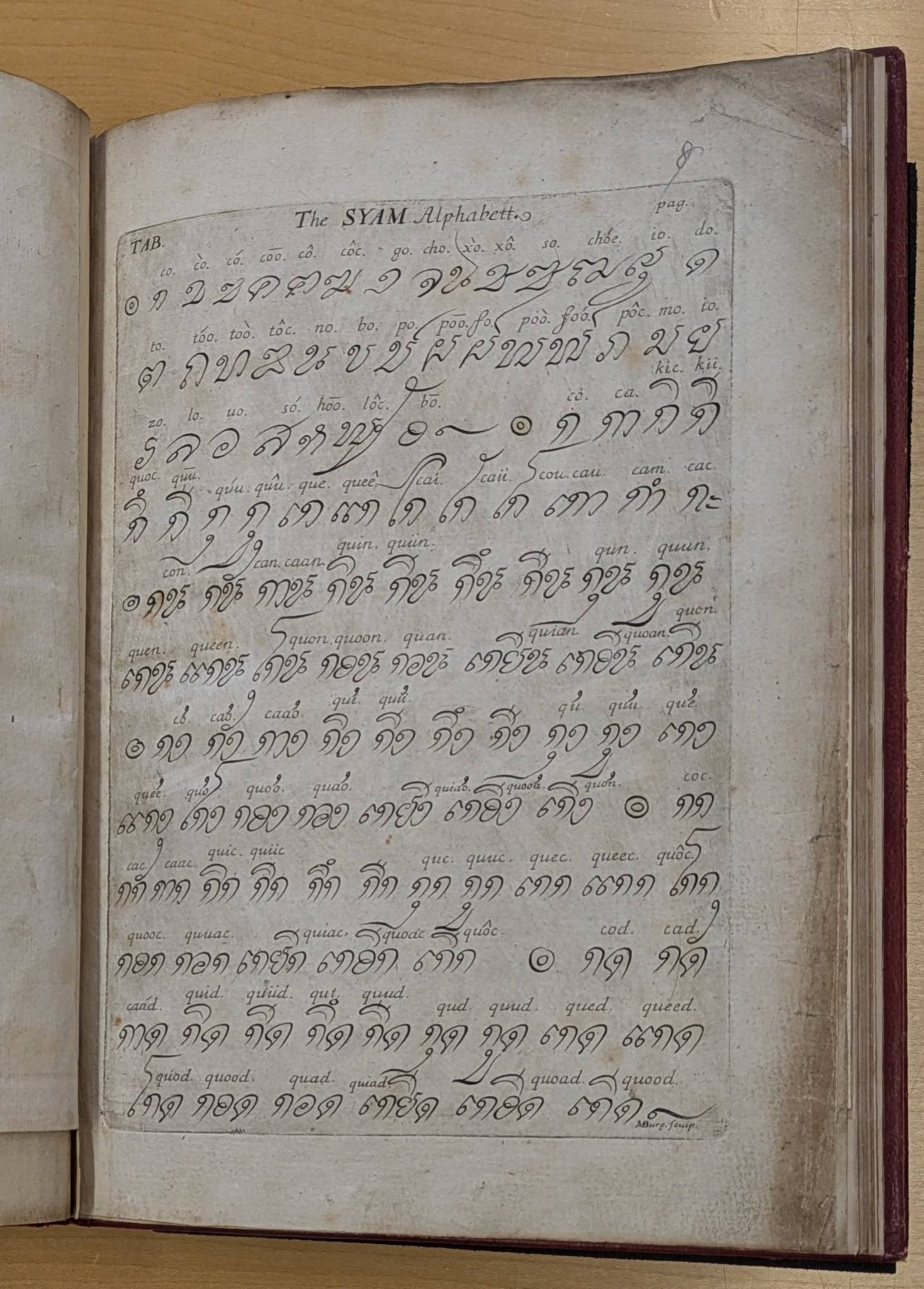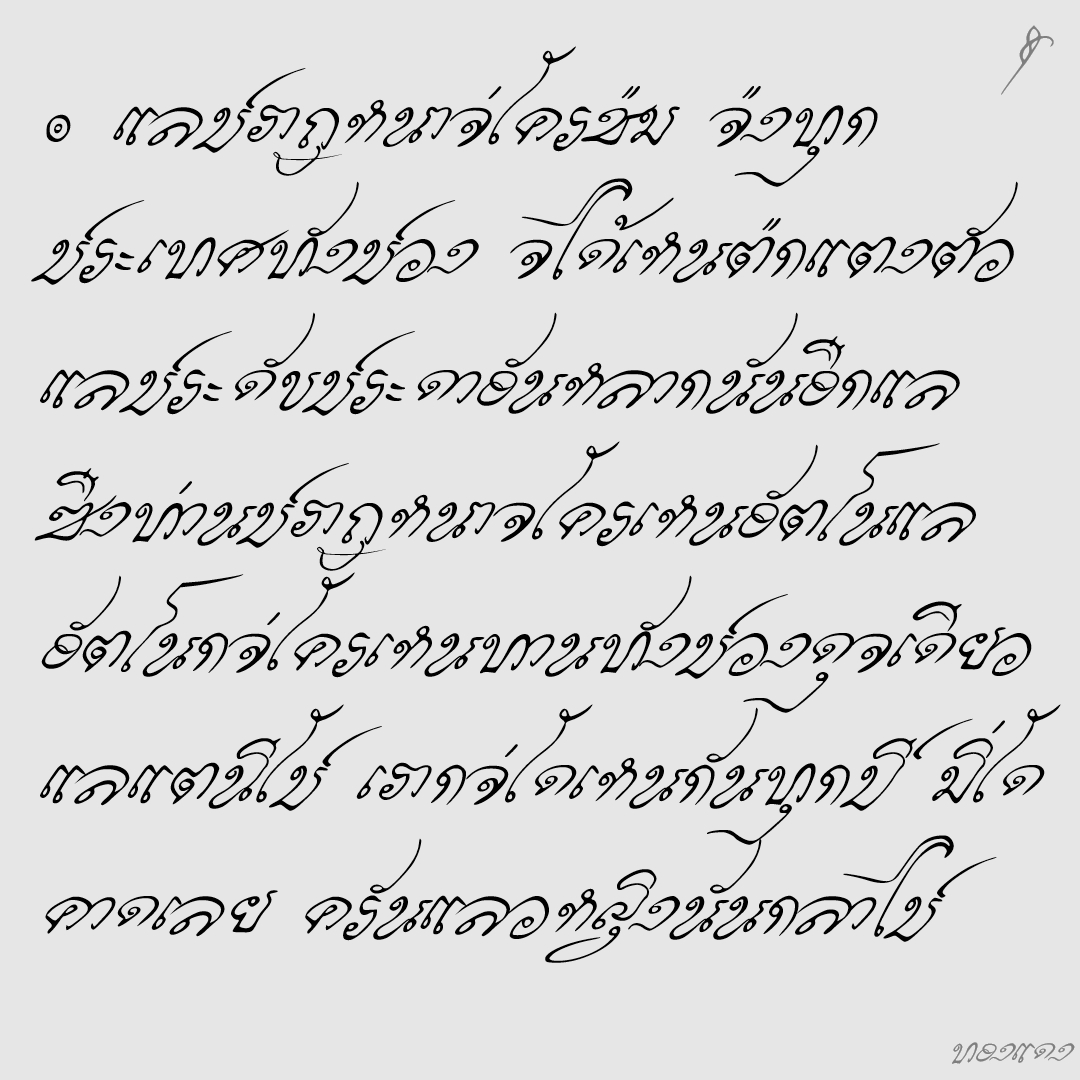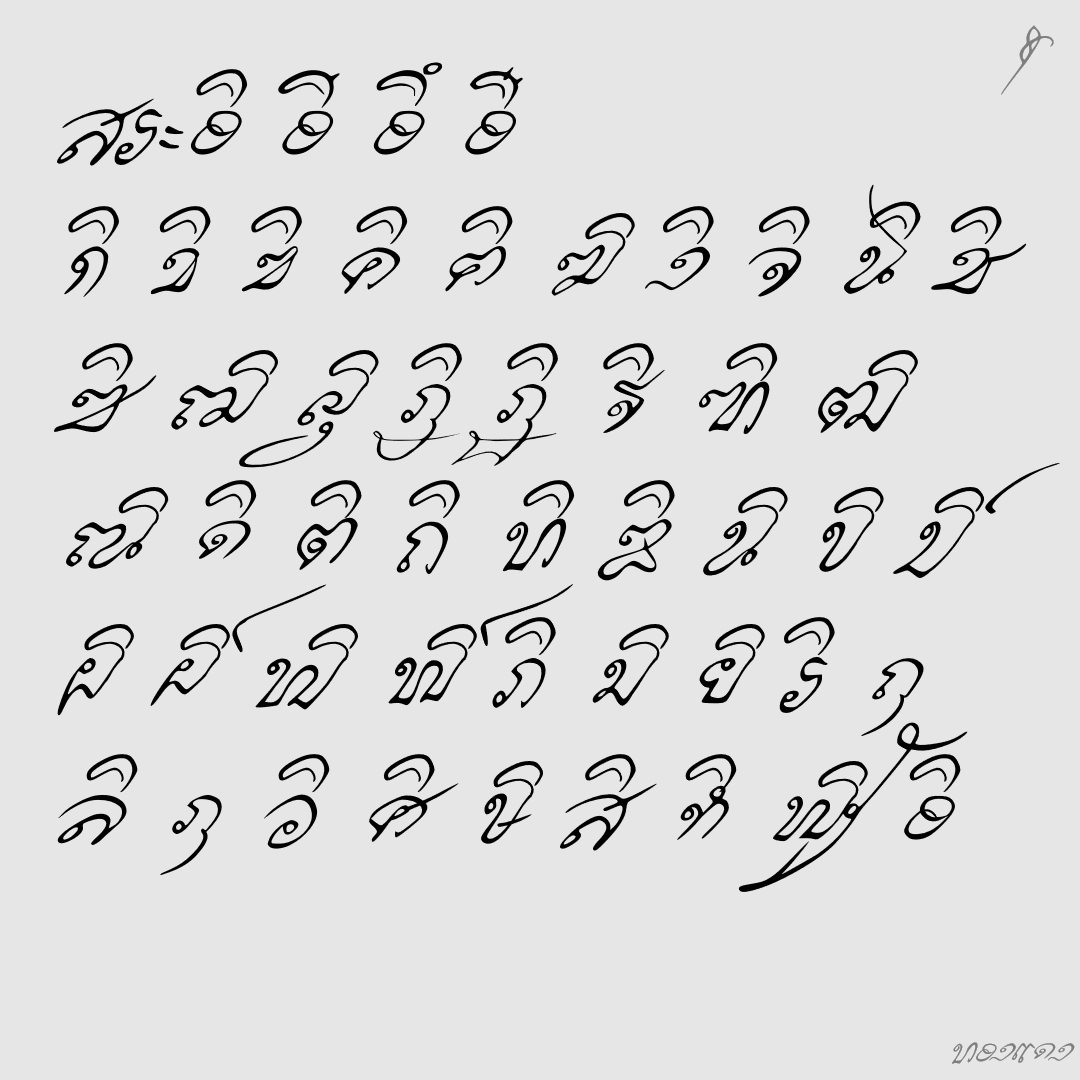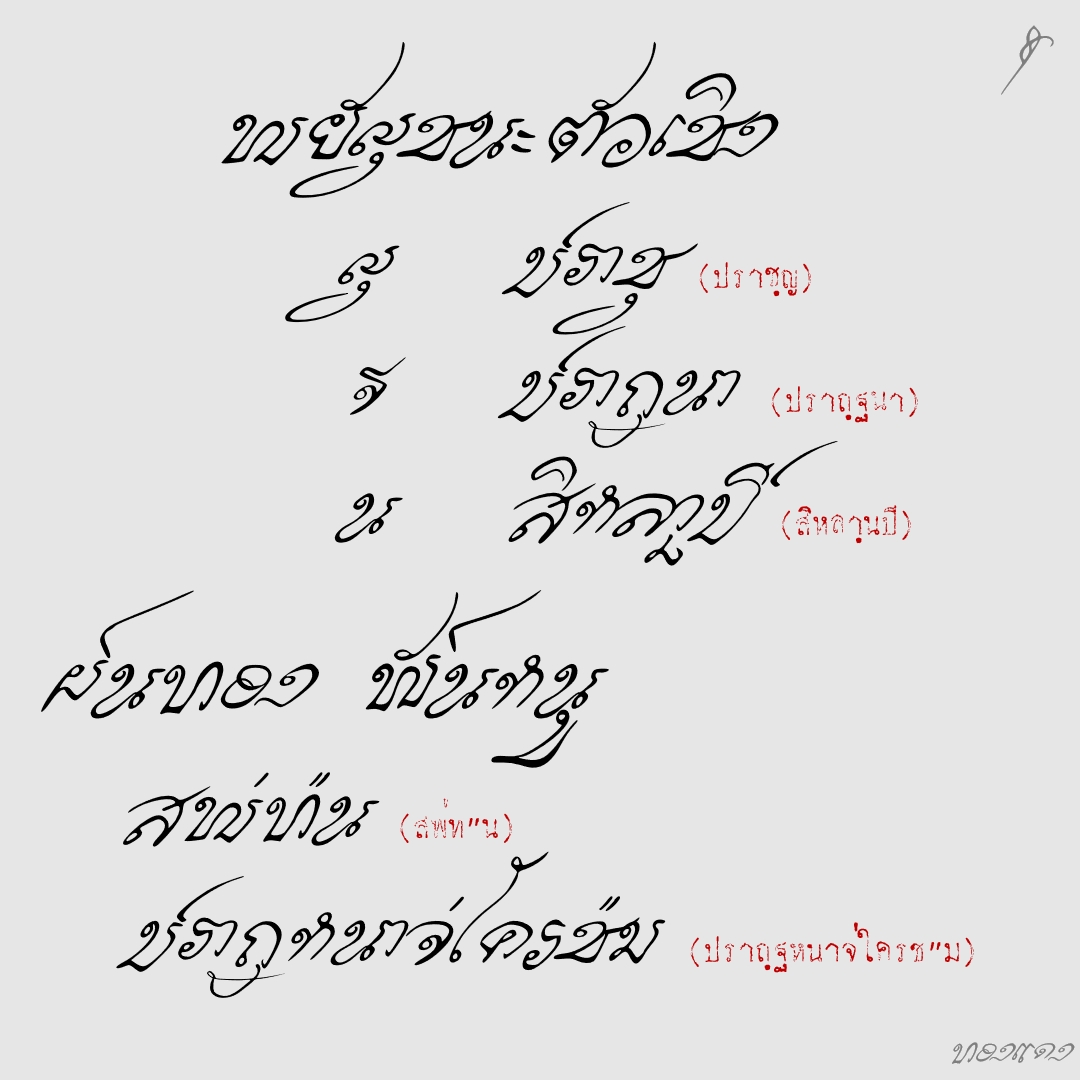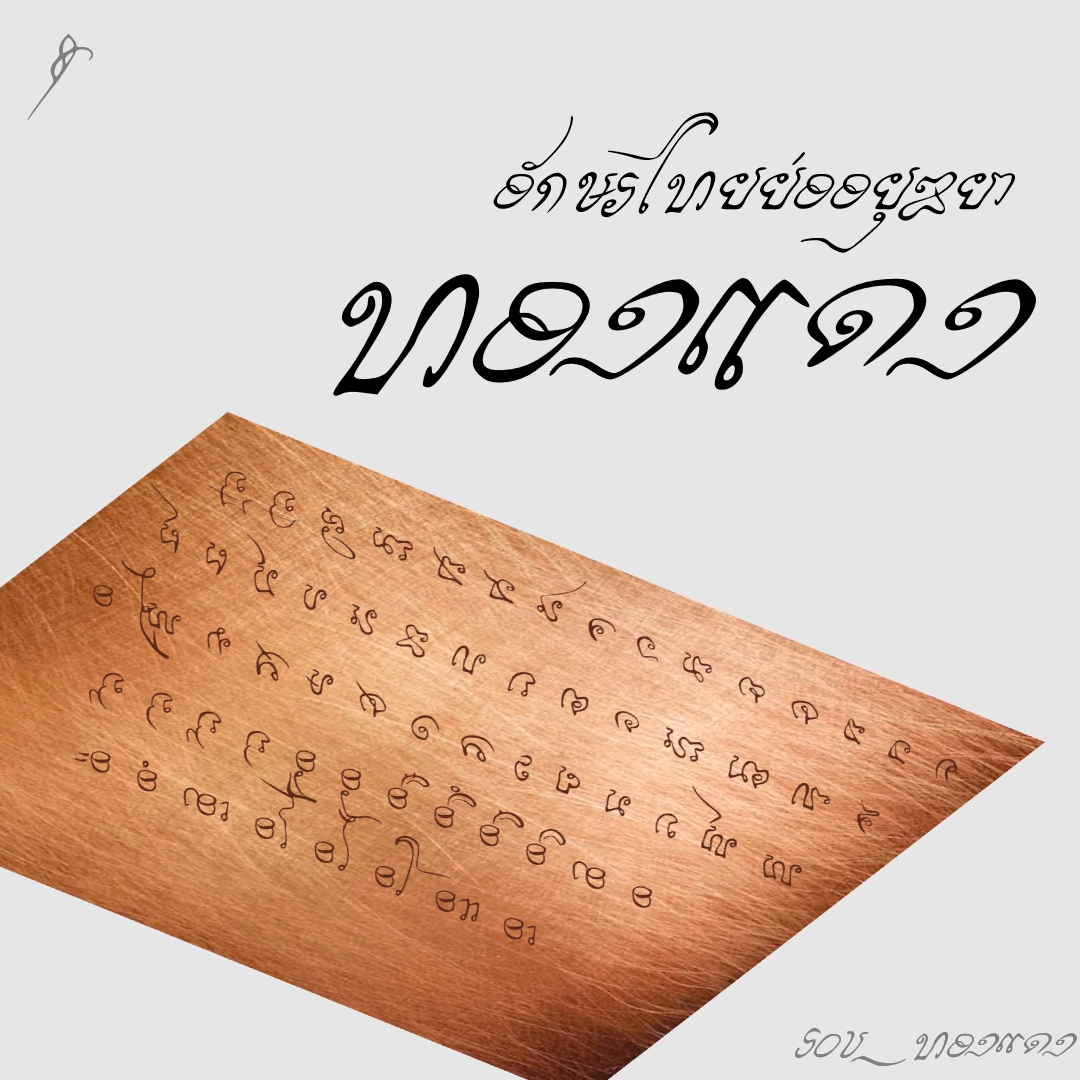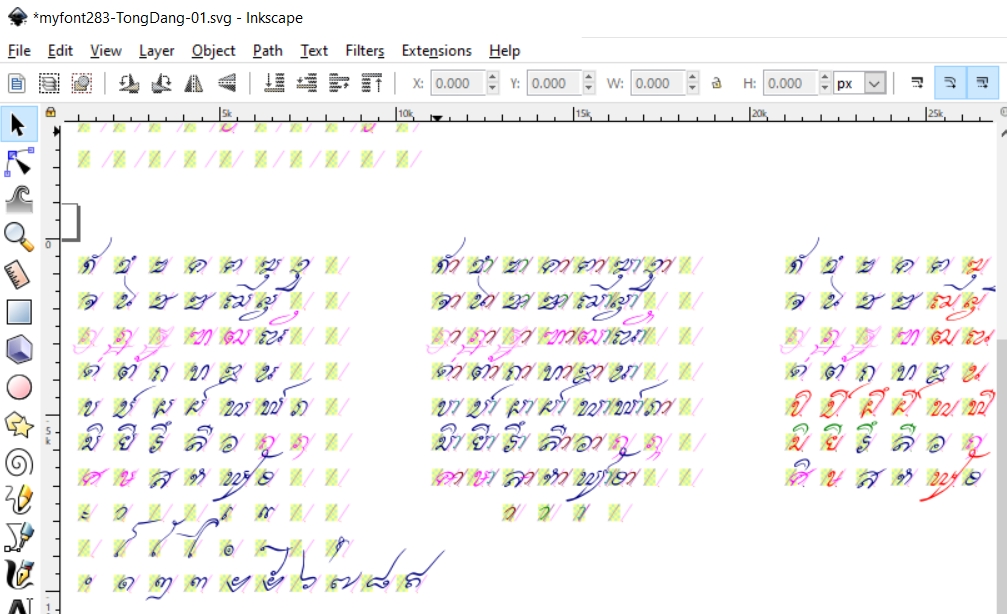
ฟอนต์ ทองแดง
ฟอนต์ทองแดง เป็นฟอนต์ที่จินตนาการว่าถ้าฝรั่งยุโรปที่เข้ามาในแผ่นดินสมเด็จพระนารายณ์ เขียนอักษรไทยอยุธยาหน้าตาน่าจะประมาณนี้ (ถ้าผู้รู้มีคำแนะนำเพิ่มเติมบอกได้นะครับ)
หมายเหตุ รูปแบบตัวอักษรหลักๆจากภาพพิมพ์ทองแดง ‘The SYAM Alphabett.’ โดย Michael Burghers เมื่อ 300กว่าปีที่แล้ว โดยอักษรดังกล่าว อ้างอิงมาจาก อักษรที่เขียนด้วยลายมือถวายพระเจ้าชาร์ลส์ที่ 2 ในปี ค.ศ.1684 แต่ในแบบดังกล่าวยังมีอักษรไม่ครบถ้วนในยุคนั้น ผมจึงได้เพิ่มอักษรเข้าไป โดยอิงจาก ‘Trois Alphabeth Siamois.’ โดย La Loubere  จดหมายเหตุลาลูแบร์พิมพ์ปี ค.ศ. 1691 ,เอกสารประชุมจดหมายเหตุออกพระวิสูทสุนทร(โกษาปาน) พ.ศ. ๒๒๓๑ (ประมาณ ค.ศ. 1688)  และนิราศต้นทางฝรงงเสษ พ.ศ. ๒๒๒๙ (ประมาณ ค.ศ. 1686)  ส่วนในวรรค ฏ ที่ไม่พบนั้น ผมจินตนาการรูปแบบอักษรขึ้นมาเองเพื่อให้ครบถ้วนตามยุคสมัย โดยอิงจากจารึกในปี พ.ศ.ใกล้เคียงกัน
ทองแดง
ชื่อฟอนต์ : ทองแดง
ฟอนต์ทองแดง เป็นฟอนต์ที่จินตนาการว่าถ้าฝรั่งยุโรปที่เข้ามาในแผ่นดินสมเด็จพระนารายณ์ เขียนอักษรไทยอยุธยาหน้าตาน่าจะประมาณนี้ (ถ้าผู้รู้มีคำแนะนำเพิ่มเติมบอกได้นะครับ)
หมายเหตุ รูปแบบตัวอักษรหลักๆจากภาพพิมพ์ทองแดง ‘The SYAM Alphabett.’ โดย Michael Burghers เมื่อ 300กว่าปีที่แล้ว โดยอักษรดังกล่าว อ้างอิงมาจาก อักษรที่เขียนด้วยลายมือถวายพระเจ้าชาร์ลส์ที่ 2 ในปี ค.ศ.1684 แต่ในแบบดังกล่าวยังมีอักษรไม่ครบถ้วนในยุคนั้น ผมจึงได้เพิ่มอักษรเข้าไป โดยอิงจาก ‘Trois Alphabeth Siamois.’ โดย La Loubere  จดหมายเหตุลาลูแบร์พิมพ์ปี ค.ศ. 1691 ,เอกสารประชุมจดหมายเหตุออกพระวิสูทสุนทร(โกษาปาน) พ.ศ. ๒๒๓๑ (ประมาณ ค.ศ. 1688)  และนิราศต้นทางฝรงงเสษ พ.ศ. ๒๒๒๙ (ประมาณ ค.ศ. 1686)  ส่วนในวรรค ฏ ที่ไม่พบนั้น ผมจินตนาการรูปแบบอักษรขึ้นมาเองเพื่อให้ครบถ้วนตามยุคสมัย โดยอิงจากจารึกในปี พ.ศ.ใกล้เคียงกัน
เล่าเรื่องเบื้องหลัง..ด้วยภาพ
1. อักษรที่เขียนด้วยลายมือถวายพระเจ้าชาร์ลส์ที่ 2 เมื่อครั้งที่ ออกขุนพิชัยวาลิต  และขุนพิชิตไมตรี เข้าฝ้าย  พระเจ้าชาร์ลส์ที่ 2 ที่ลอนดอนในปี ค.ศ.1684
2. นิราศต้นทางฝรงงเสษ ปี ค.ศ. 1686
3. บันทึกรายวันของโกษาปาน ปี ค.ศ. 1688
4. ภาพอักษรไทยในหนังสือ Du Royaume de Siam โดย Simon de la Loubère  ตีพิมพ์ปี ค.ศ.1691
5. ภาพอักษรจากพิมพ์ทองแดง ก่อนปี ค.ศ. 1700
เหล่านี้เป็นส่วนหนึ่งของ เอกสารประกอบ  เพื่อประกอบเป็นฟอนต์นี้  จริงๆใช้หนังสืออีกหลายเล่ม
BTS เล่าเรื่องรวบเหลือฟอนต์เดียว
- เดิมที่จะทำฟอนต์  ‘Trois Alphabeth Siamois.’  และ  ‘The SYAM Alphabett.’ โดยเพิ่มความสามารถในการเขียนอักขรแบบไทยอยุทธยาเข้าไป  แถมด้วยตัวบาลีที่มีต้นแบบในจดหมายเหตุลาลูแบร์  แต่ก็ติดกรอบเดิมว่าอักษรไม่ครบถ้วน จะด้นอักษรเข้าไปเยอะๆก็ดูบิดเบือนไปมากเพราะอ้างจากเอกสารจริง
- อันที่จริง ก็ได้ทำครบทุกตัวอักษร ‘Trois Alphabeth Siamois.’ ทั้งตัวไทยและบาลี แถมตัวละตินด้วย (มีเอกสารอ้างอิงด้วยทั้งไทยและบาลี แต่ติดนิดหน่อยที่บาลีตัวเชิงยังไม่สามารถยืนยันศักราชของเอกสารได้)
- พอมาเจออักษรจากพิมพ์ทองแดง โดย Michael Burghers ซึ่งเห็นว่าเป็นการดัดแปลงมาตั้งแต่ต้น จึงนำมาต่อยอดดัดแปลงให้ครบทุกตัวอักษร เสียแต่ว่าต้องทิ้งตัวบาลีไป
ตัวอย่างลายมือของชาวต่างชาติในสมัยพระนารายณ์ที่น่าสนใจคือ สัพพัญญูทางภาษาอย่าง หลุยส์ ลาโน ซื่งเป็นสังฆราชองค์แรกในสยาม ท่านสนใจทั้งภาษาไทยและบาลี ลายมือก็สวยงามมากครับ ผมได้แสดงตัวอย่างไว้ในหนังสือ "อักษรสยาม" อยู่บ้าง แต่ตัวฟ้อนต์ยังไม่เรียบร้อยดี ซึ่งหวังว่าอาจได้เผยแพร่ในอนาคตนะครับ